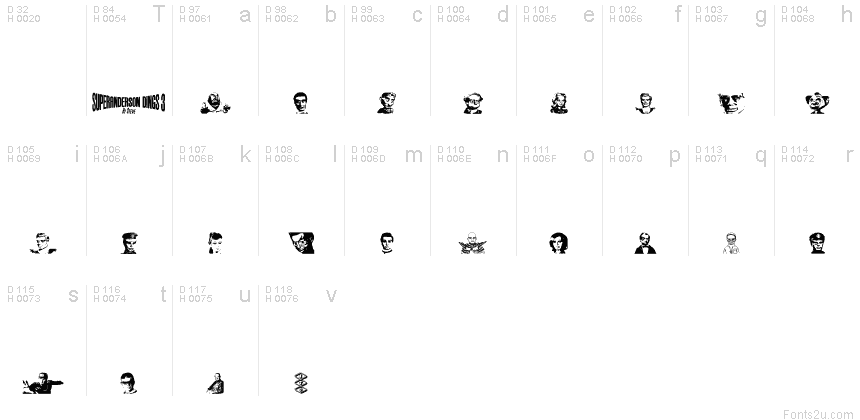
Anderson Dings 3 od Superanderson Dings3 to darmowy font typu dingbat, pełen komiksowych postaci i twarzy. Każdy znak wygląda jak rysunek odręczny – grube czarne kreski, przesadzone miny i lekko nierówne krawędzie sprawiają wrażenie, jakby pochodziły prosto ze szkicownika. Wstaw jedną ikonę w rogu strony, aby błyskawicznie nadać jej charakteru, lub powtórz je w formie wzoru, by uzyskać żywą, zabawną teksturę.
Używając Anderson Dings 3, możesz szybko dodawać oryginalne grafiki do plakatów, komiksów, materiałów szkolnych, naklejek, postów w social mediach czy zaproszeń, bez konieczności używania tabletu graficznego. Ikony są czytelne nawet w małych rozmiarach, ale najlepiej wyglądają, gdy powiększysz je jako wyrazisty element graficzny. Aby uzyskać przejrzysty i czytelny efekt, połącz ten darmowy krój z prostym fontem bezszeryfowym i pozwól, by dingbaty nadały całości wyrazu.